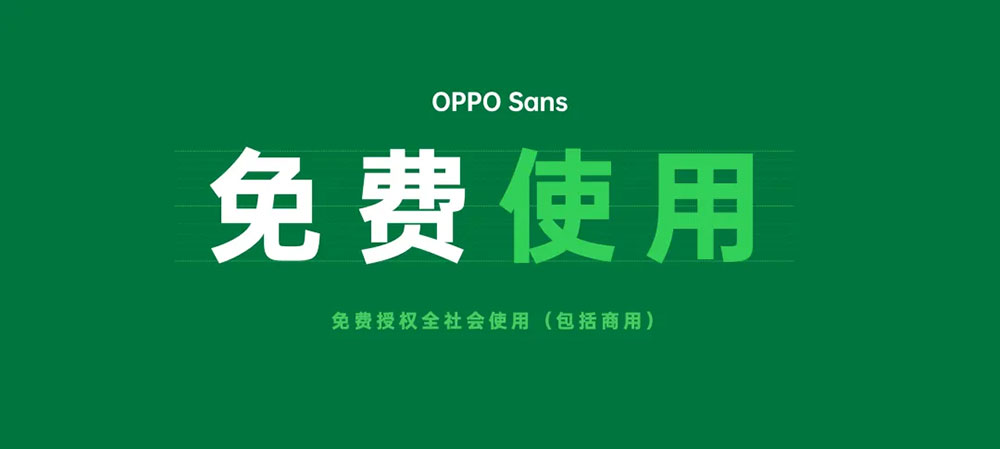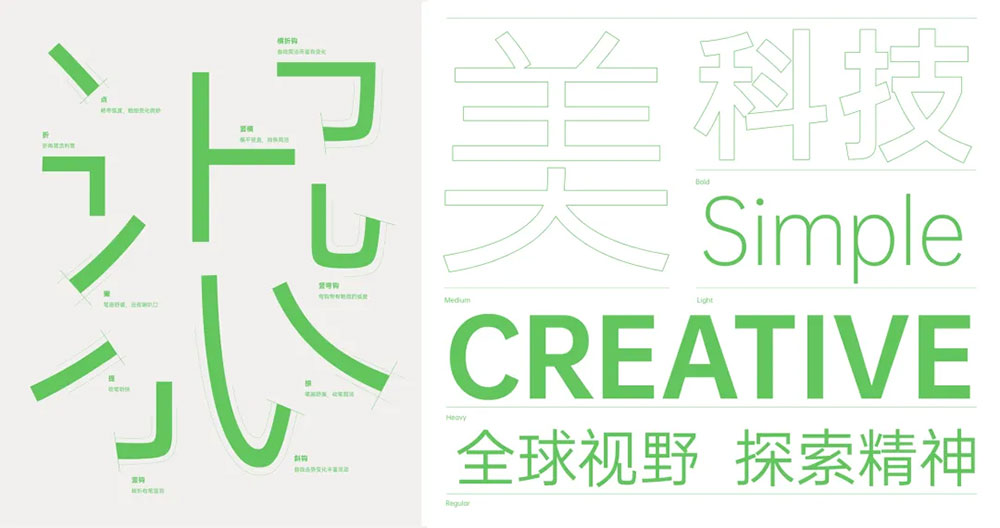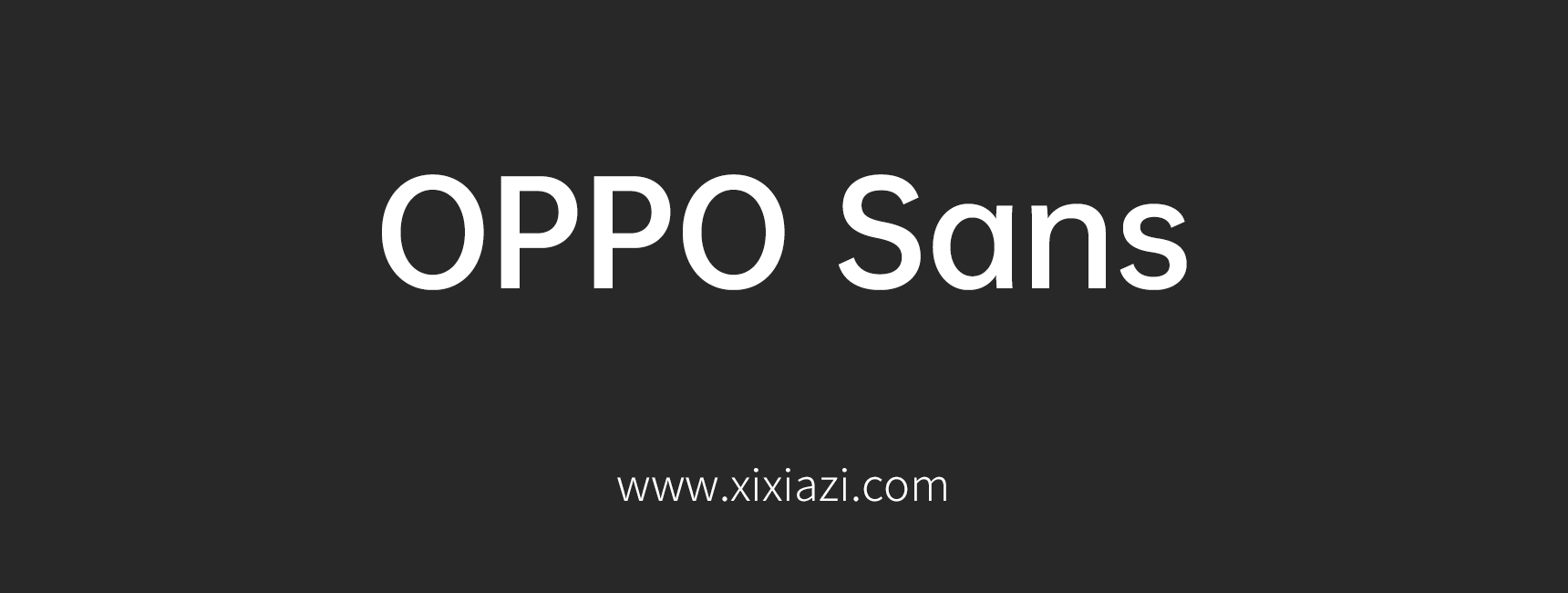
OPPO Sans
OPPO Sans 自 2019 年发布以来,已获得大量行业与用户的积极评价。为了给用户带来更舒适的屏幕阅读体验,OPPO Sans 4.0 融合了用于阅读的 Text 字体和用于展示的 Display 字体的特征,这样既秉承过往稳定舒展的字形便于阅读,又进一步提升了字体的表现力。